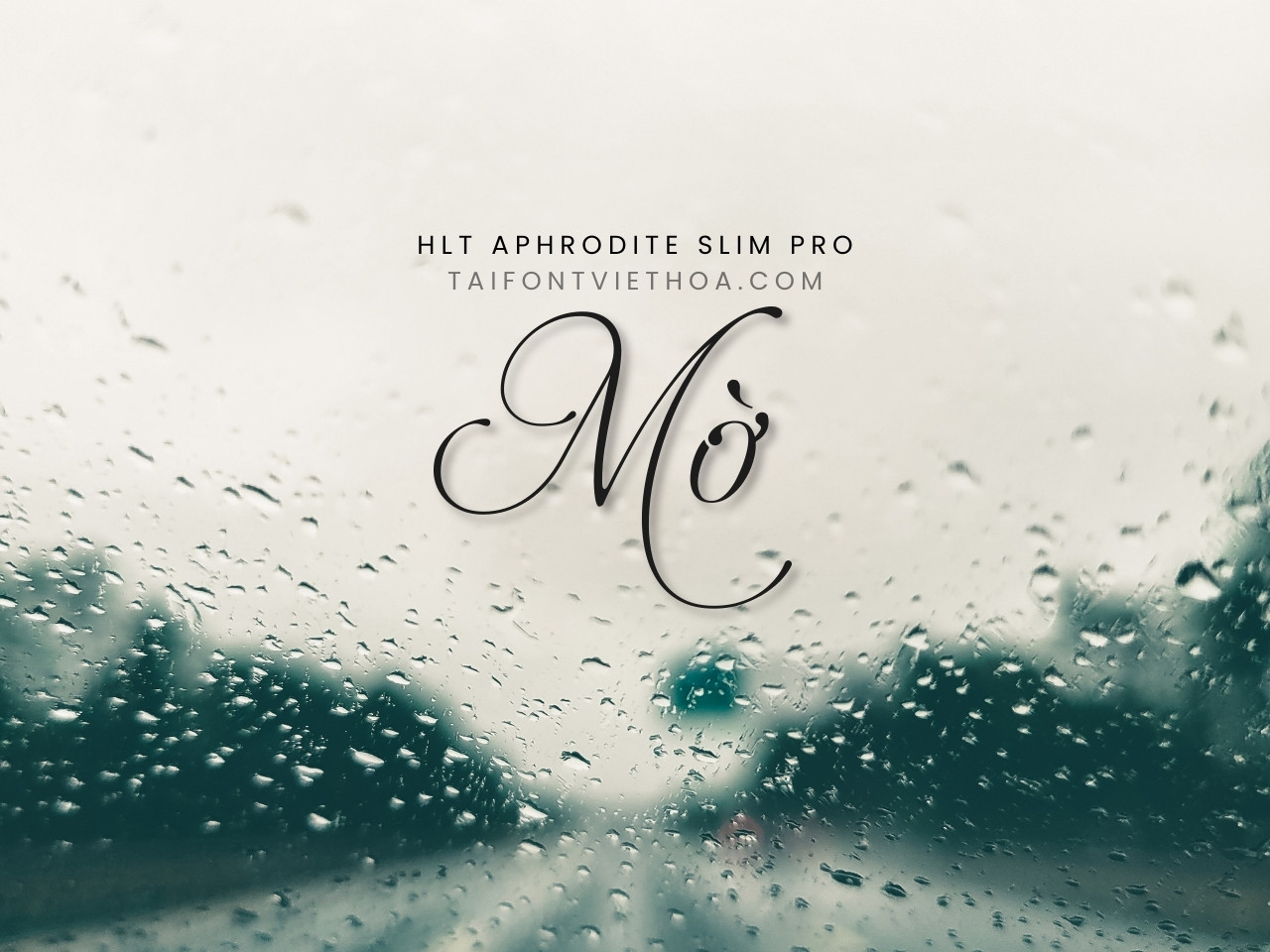
Giới thiệu về font HLT Aphroditeslimpro – Nét duyên dáng của nghệ thuật thư pháp hiện đại
HLT Aphroditeslimpro là bản Việt hóa hoàn chỉnh của font gốc “Aphrodite Slim Pro” – một kiểu chữ script được phát triển bởi nhà thiết kế Sabrina Mariela Lopez và phát hành bởi Sudtipos, hãng font nổi tiếng đến từ Argentina. Với cảm hứng từ thư pháp cổ điển, kết hợp kỹ thuật typographic đương đại, font này mang lại sự mềm mại, uyển chuyển và có tính ứng dụng nghệ thuật cao. Bản gốc hỗ trợ hơn 50 ngôn ngữ sử dụng bảng chữ cái Latinh, phù hợp cho các dự án toàn cầu.
Phiên bản Việt hóa được thực hiện bởi đội ngũ HLT Fonts, đảm bảo giữ nguyên linh hồn thiết kế qua từng đường nét, đồng thời tối ưu hóa khả năng hiển thị tiếng Việt với đầy đủ dấu và ký tự đặc trưng Unicode. Quá trình Việt hóa không chỉ đơn thuần là bổ sung ký tự mà còn điều chỉnh tỉ lệ, khoảng cách chữ để đảm bảo trải nghiệm thẩm mỹ nhất. Font này hiện đã được taifontviethoa.com chọn lọc, kiểm duyệt và chia sẻ nhằm phục vụ cộng đồng thiết kế Việt trong các dự án chuyên nghiệp và cá nhân đậm chất nghệ thuật.
Đặc điểm thiết kế nổi bật và ứng dụng thực tế của HLT Aphroditeslimpro
Font HLT Aphroditeslimpro sở hữu cấu trúc chữ thanh mảnh với đường nét uốn cong tinh tế, ligatures (liên kết chữ) được thiết kế công phu, tạo cảm giác tuôn trào như những nét bút tay nghệ thuật. Các ký tự có độ dài biến thiên, mang đến khả năng tuỳ biến cao và cảm xúc thị giác mạnh mẽ. Nhờ đó, font này đặc biệt thích hợp cho các thiết kế có yếu tố cảm xúc và phong cách lãng mạn.
HLT Aphroditeslimpro lý tưởng để sử dụng trong thiệp cưới, thư mời, nhận diện thương hiệu thời trang, logo mỹ phẩm, bìa sách văn học hoặc các thiết kế quảng bá sản phẩm dành cho phụ nữ. Font cũng phù hợp với các ấn phẩm truyền thông mang phong cách sang trọng, nhẹ nhàng và nữ tính.